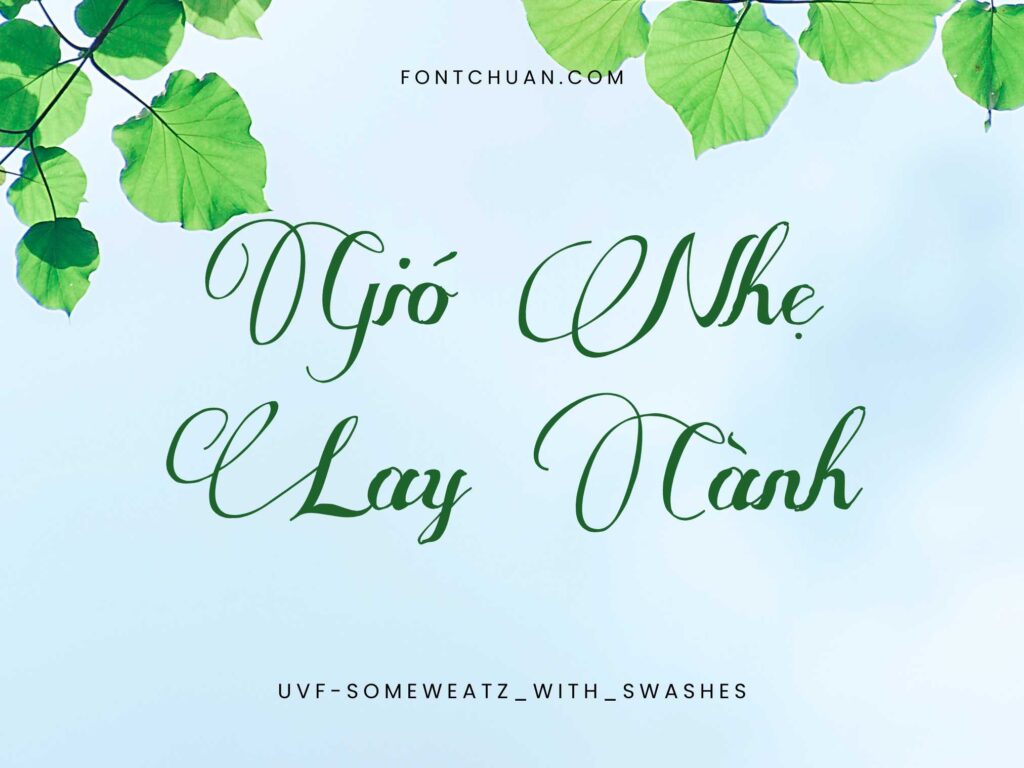
Font UVF Some Weatz Swashes Việt Hóa
Some Weatz Swashes là một phông chữ viết tay được thiết kế bởi Måns Grebäck, nổi bật với các đường nét uyển chuyển và trang trí tinh tế. Phông chữ này mang lại cảm giác thanh lịch và nghệ thuật, phù hợp cho các thiết kế cần sự mềm mại và sáng tạo. Với các ký tự hoa mỹ và swash độc đáo, Some Weatz Swashes tạo nên sự thu hút đặc biệt trong các dự án thiết kế.
Phông chữ này phù hợp cho các ứng dụng như thiệp mời, tiêu đề sách, thiết kế logo và các ấn phẩm nghệ thuật. Trong lĩnh vực sự kiện, Some Weatz Swashes có thể được sử dụng trong các dịp như lễ hội, lễ cưới và các sự kiện văn hóa. Ngoài ra, phông chữ này cũng thích hợp cho các ngành nghề như thiết kế đồ họa, nghệ thuật trang trí và xuất bản.